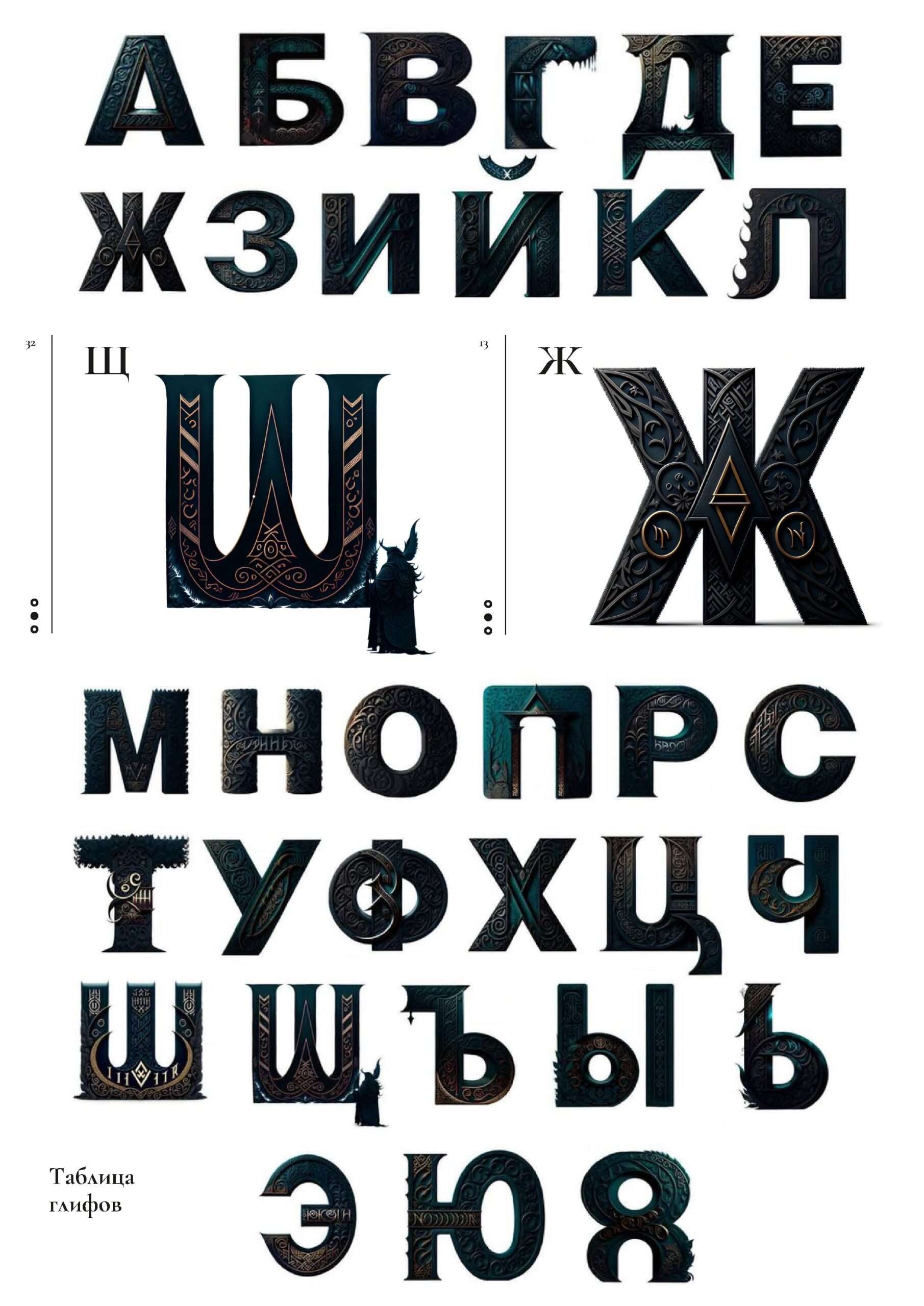
Шрифт по скандинавской мифологии
Настроение: тёмное, мифическое, холодное.
Шрифт: готический, средневековый, рунический.
Цель: передать с помощью шрифта мифическую и холодную атмосферу скандинавской мифологии. Использование образов, миров и мотивов.
Язык: кириллица.